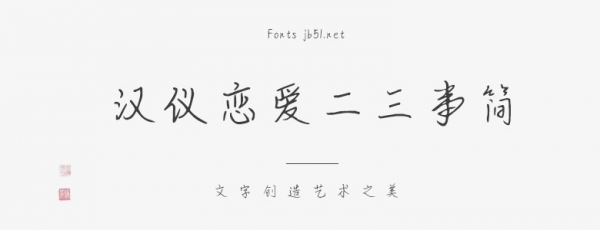
漢儀戀愛二三事簡(jiǎn)是由漢儀字庫(kù)出品,字體筆觸纖細(xì),書寫流暢,具有很好的視覺感,適合應(yīng)用于藝術(shù)設(shè)計(jì)、平面宣傳設(shè)計(jì)、網(wǎng)頁(yè)設(shè)計(jì),書法字帖等領(lǐng)域,需要的朋友可以前來本站下載。